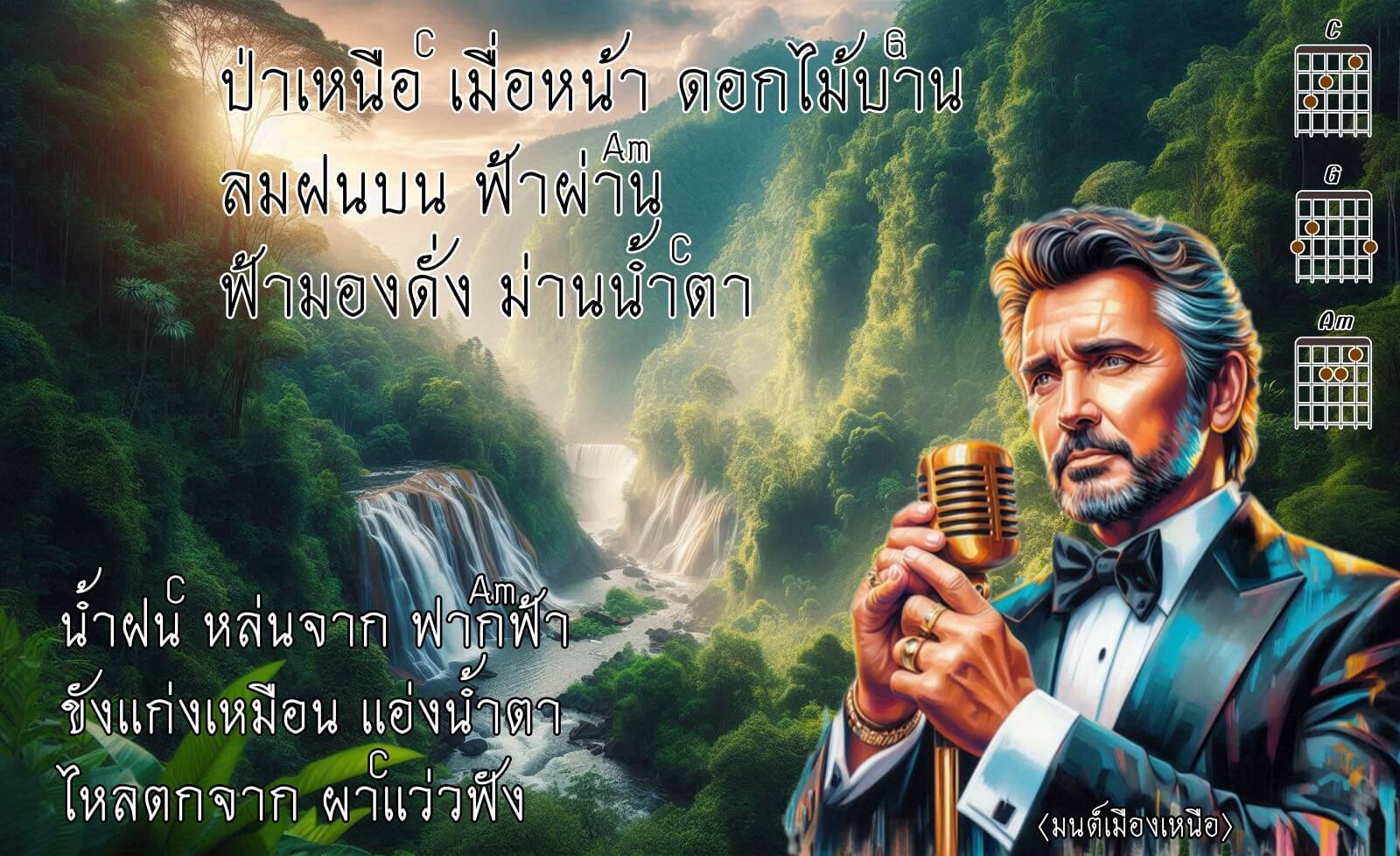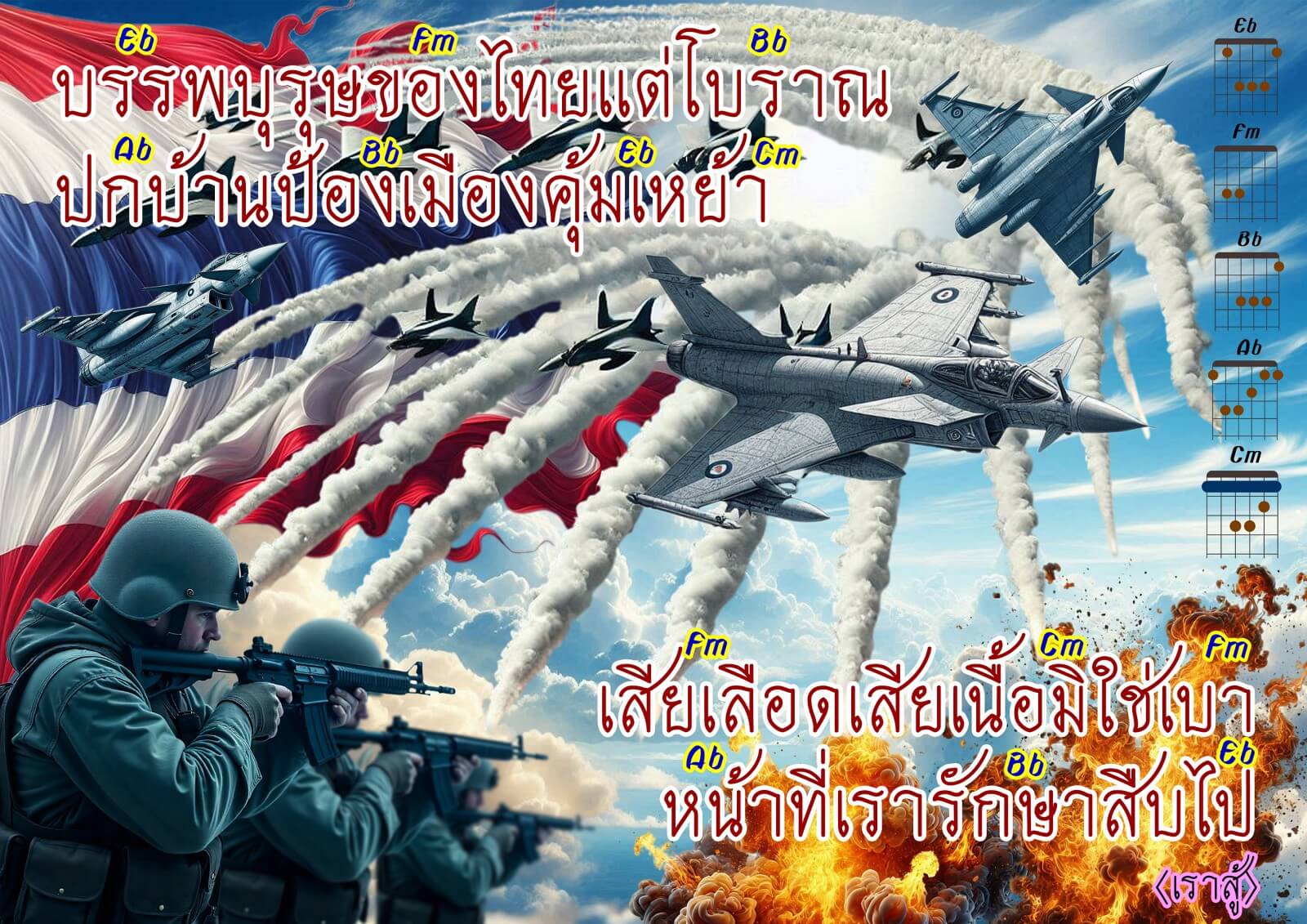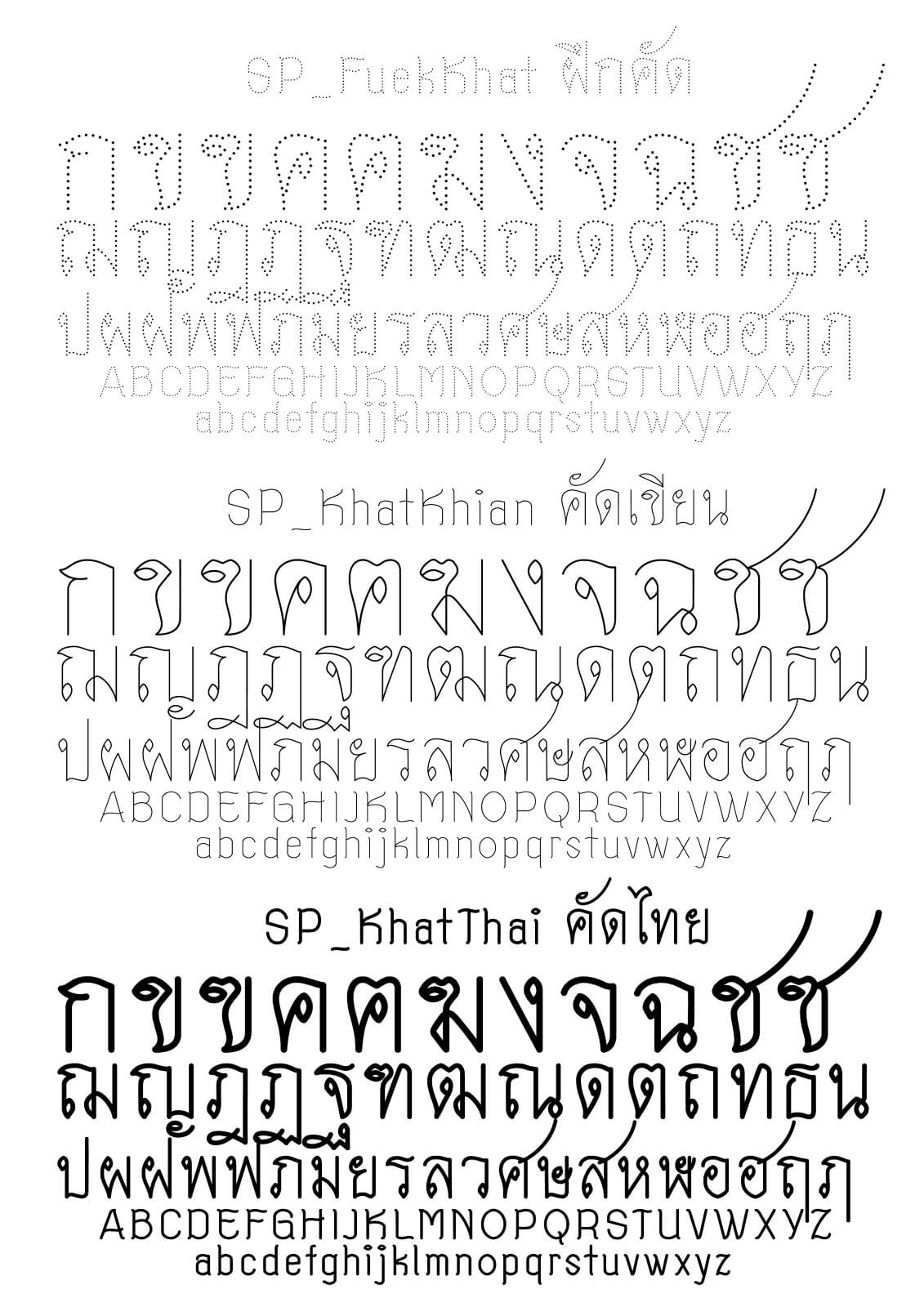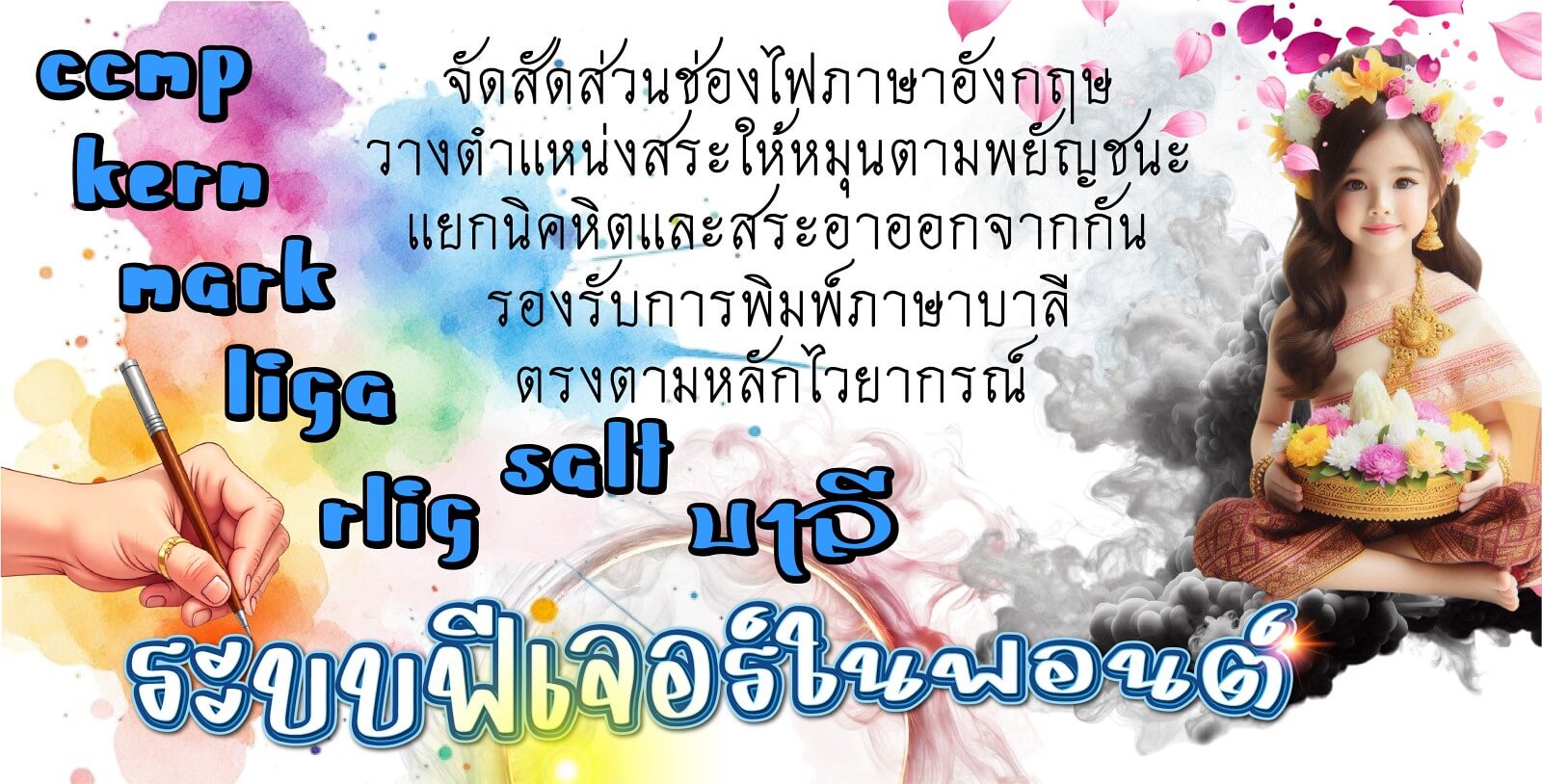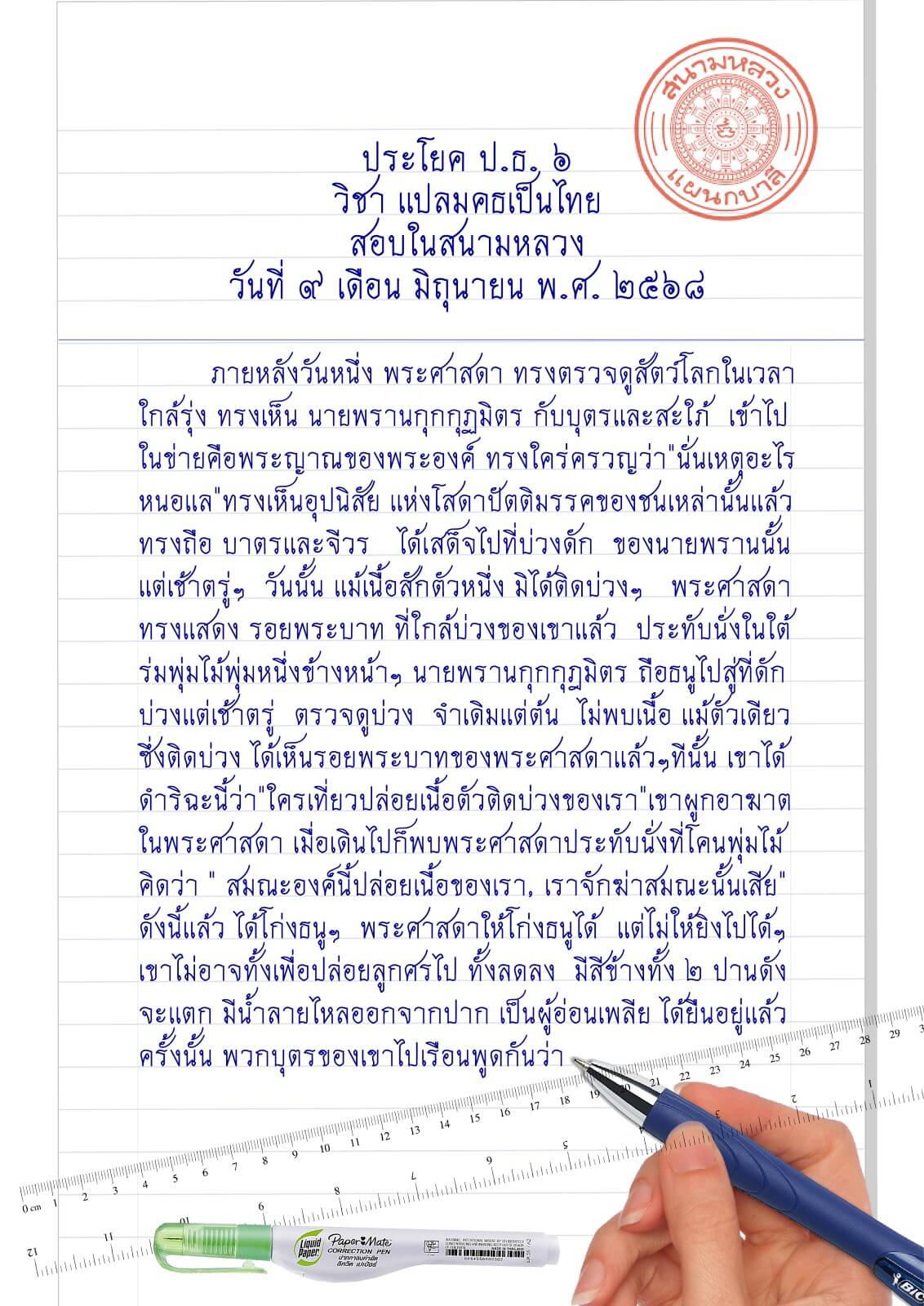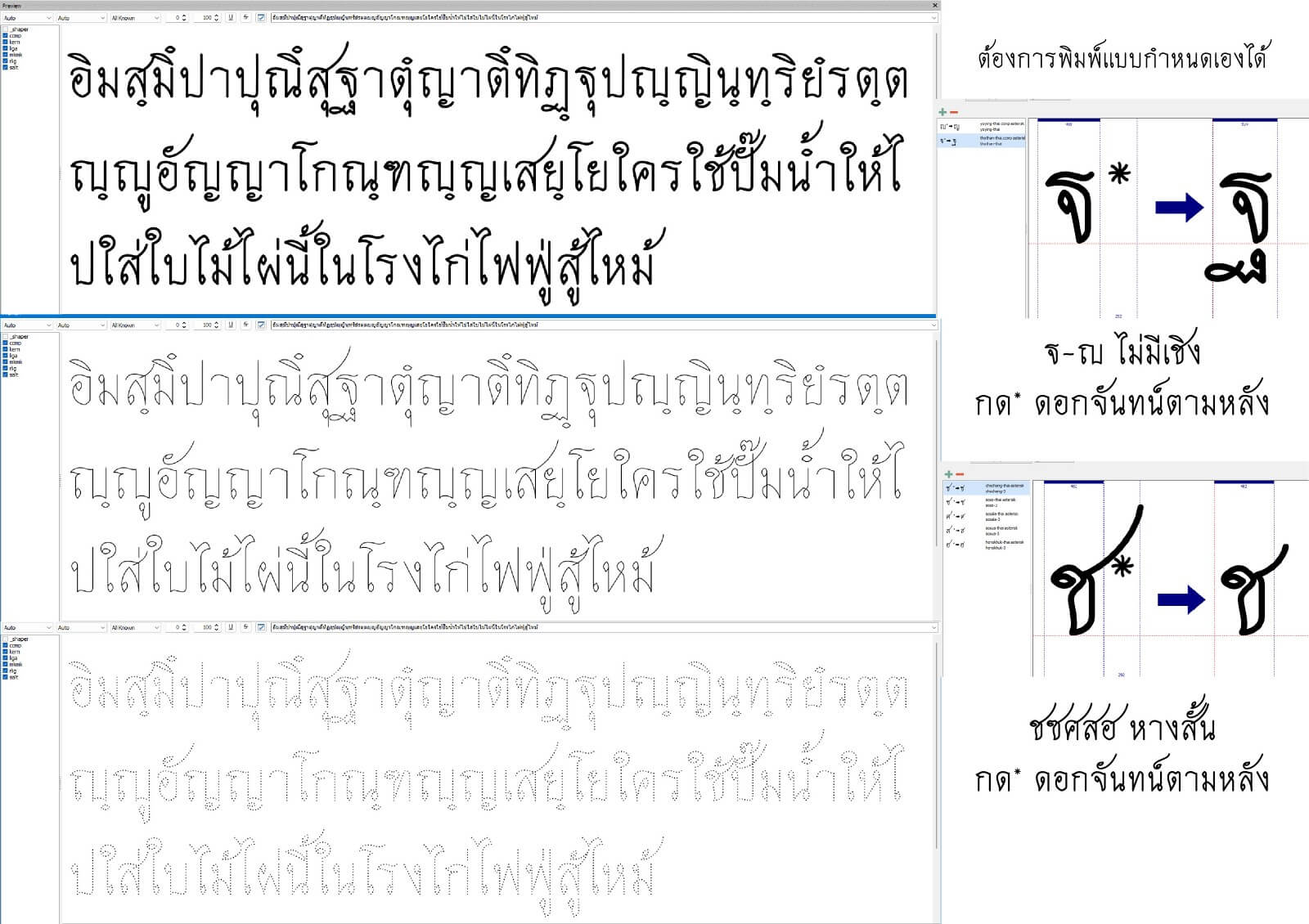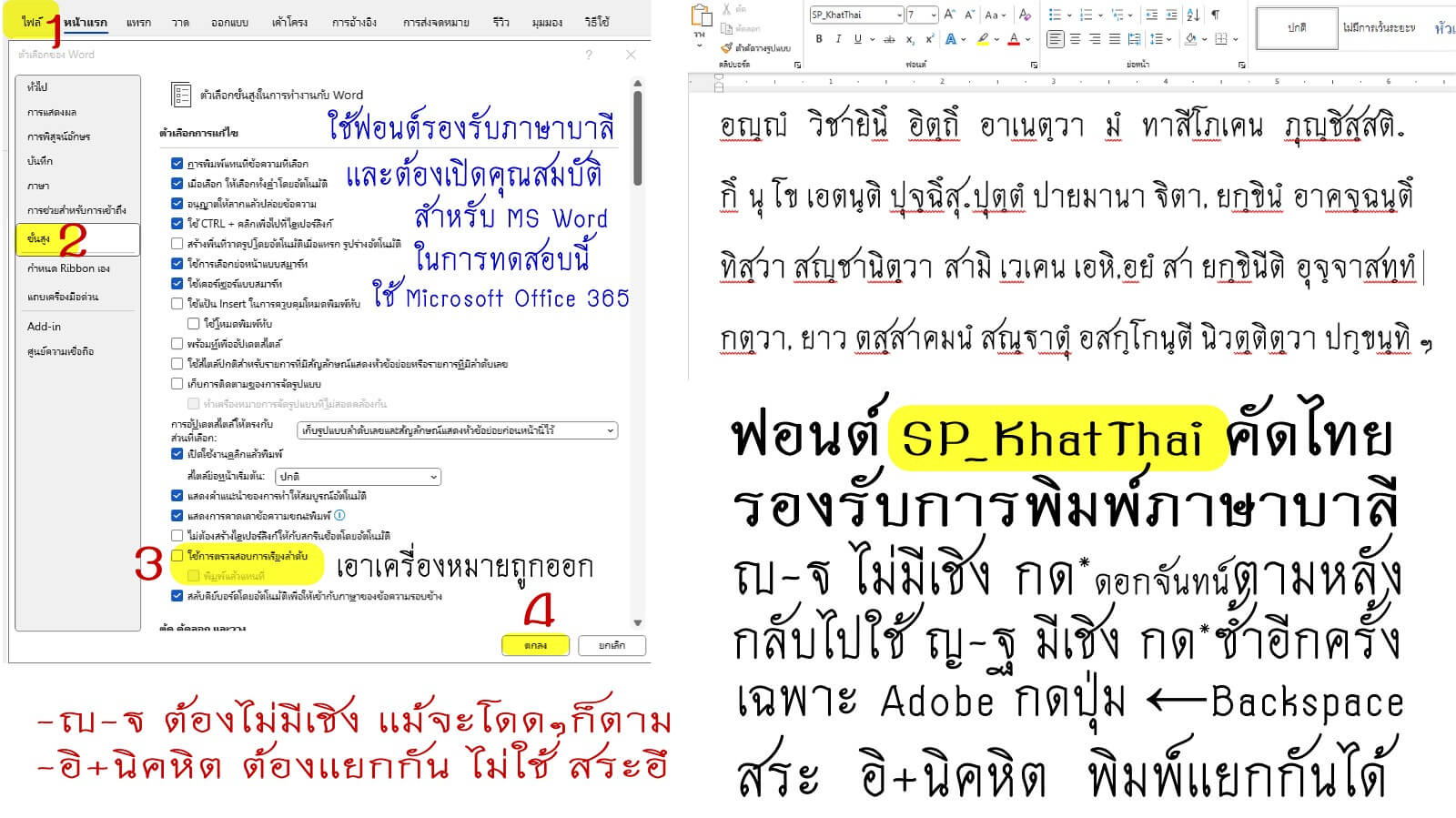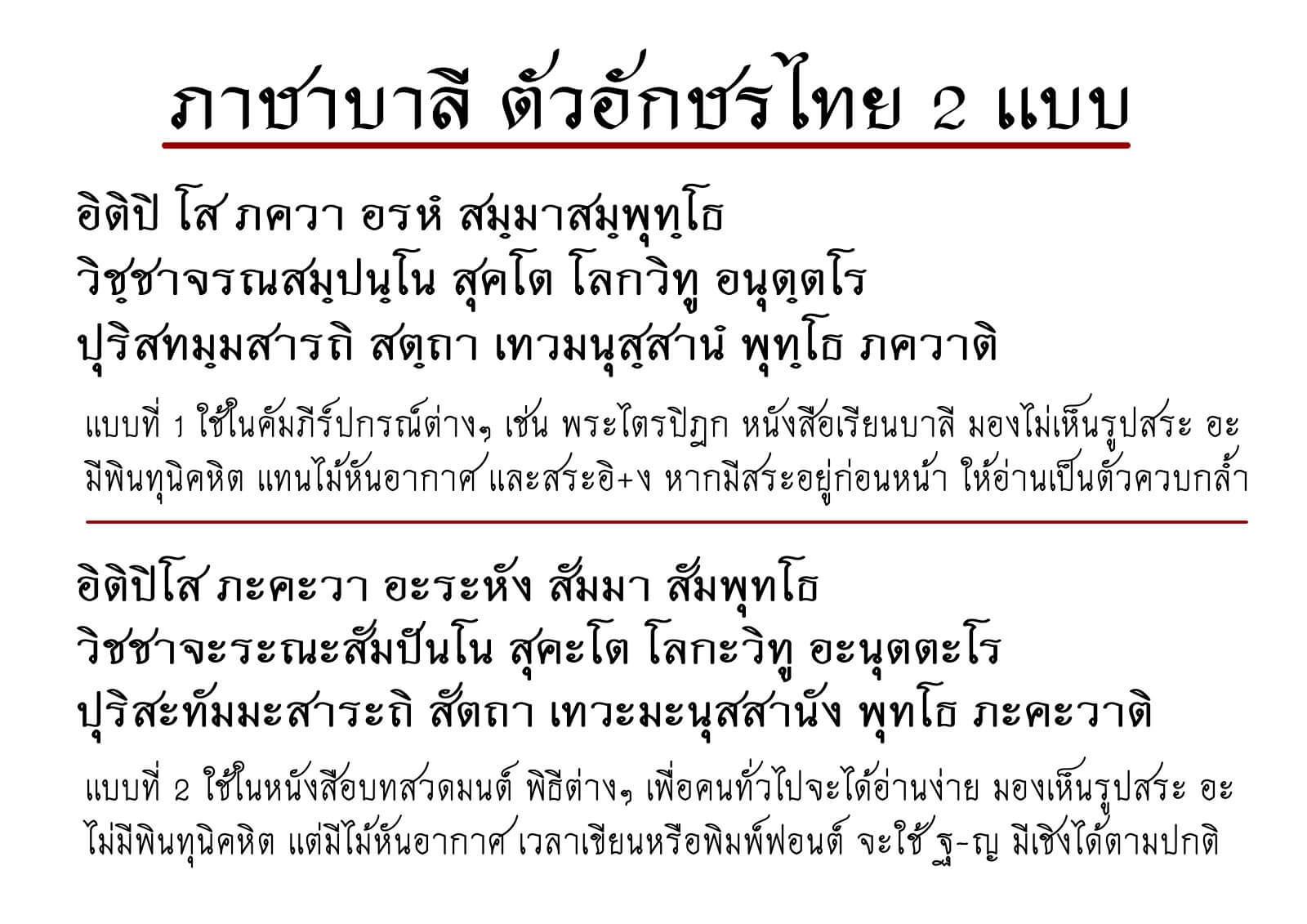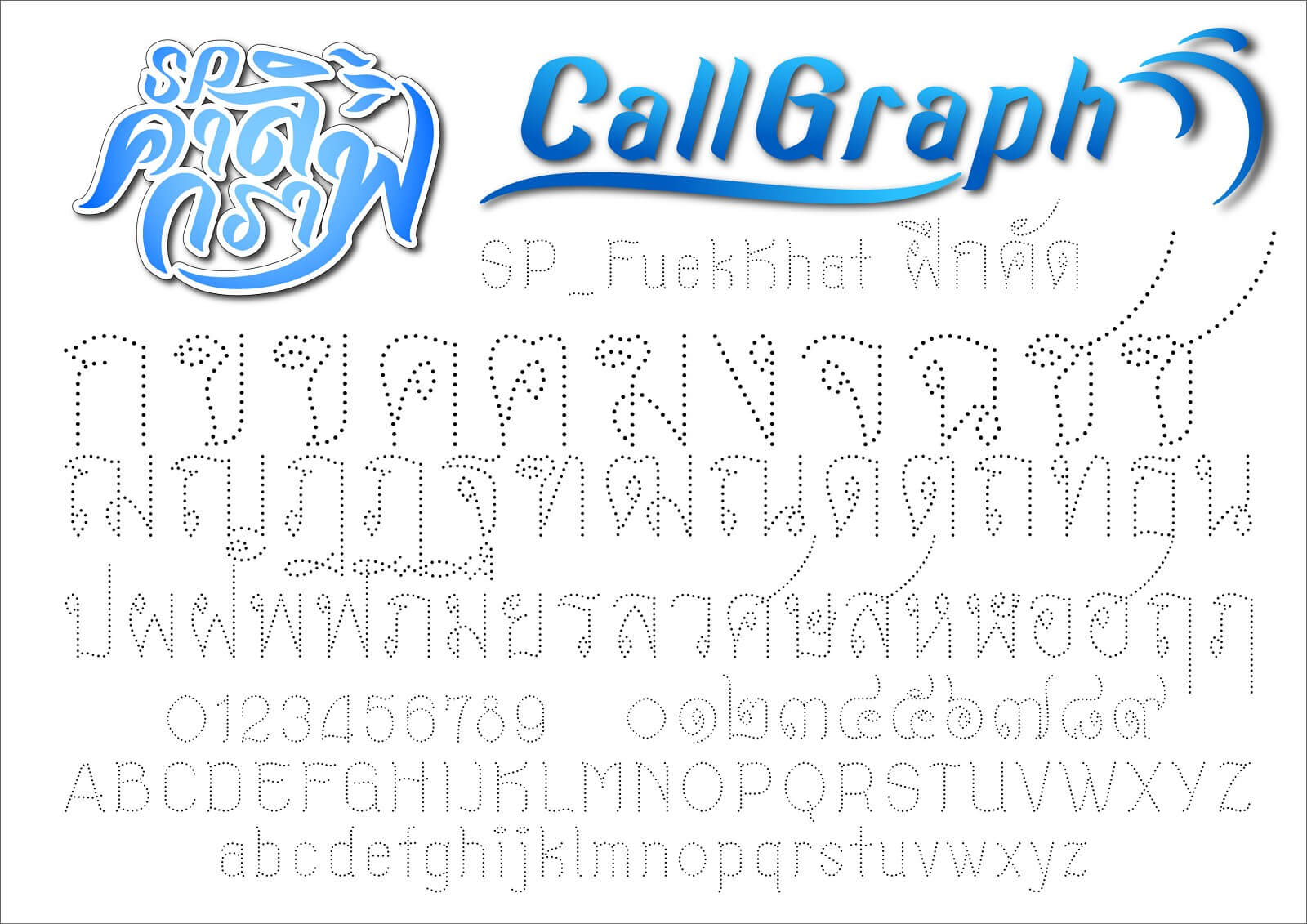
คัดไทย-คัดเขียน-ฝึกคัด
แจกฟรี ฟอนต์คัดลายมือ คัดไทย (SP_KhatThai) / คัดเขียน (SP_KhatKhian) / ฝึกคัด (SP_FuekKhat) / ยู่ยี่ (SP_YuYi) จัดหนักไม่ต้องขอ โดย SP_Font คาลิกราฟ Ep.1
อักษรที่บ่งชี้ถึงอัตลักษณ์ความเป็นไทย ใจรักสงบ เป็นคนมีน้ำใจ ใฝ่สำนึกรู้คุณ รู้จักยกย่องสรรเสริญ เชิดชู ให้เกียรติกัน เป็นตัวหนังสือที่ใช้คัดเขียนข้อสอบตั้งแต่สมัยโบราณ มีคนนิยมใช้เขียนกันแพร่หลาย
บัดนี้ ถึงเวลานำมาสู่ฟอนต์ลายมือคัดไทย ที่จัดอาวุธหนัก คือระบบ Features Font ล็อกเป้าเข้าพิกัด มีเรดาร์ตรวจหลบหางยาว หลีกเลี่ยงการปะทะกันของสระ-พยัญชนะ ปกป้องรักษาการละเมิดในที่ทับซ้อน มีการจัดสระวรรณยุกต์ทุกชั้น รวมทั้งจัดช่องไฟอักษรละตินให้เป็นระเบียบเรียบร้อยดีงาม เป็นไปตามมาตรการขั้นสูงสุด
ทั้งนี้ยังแยกนิคหิตกับสระอาออกจากกันให้เป็นเอกเทศต่างหาก ไม่ขึ้นตรงอาศัยกับสระอำ สามารถพิมพ์ภาษาบาลี (อักษรไทย) ได้ถูกต้องตามหลักไวยากรณ์
คัดไทย (SP_KhatThai)
คัดเขียน (SP_KhatKhian)
ฝึกคัด (SP_FuekKhat)
หากฝึกเขียนไม่ผ่าน… จัดการบอมบ์เลย ด้วย ยู่ยี่ (SP_YuYi)